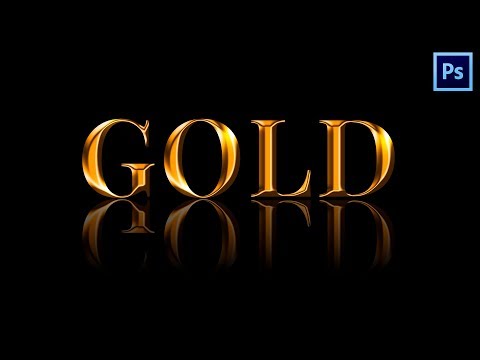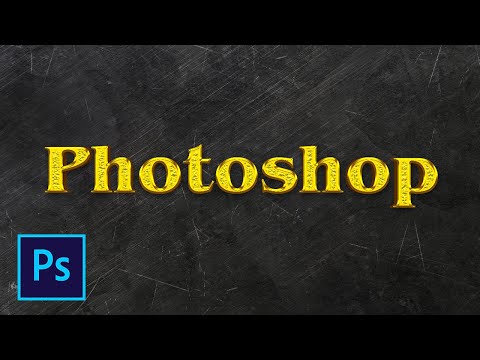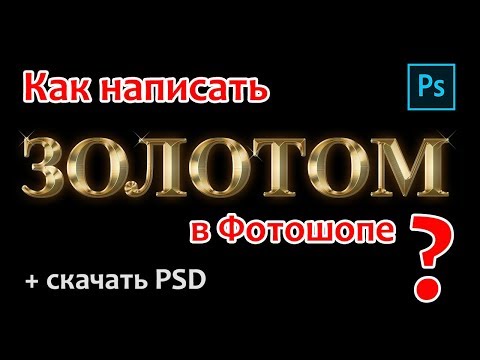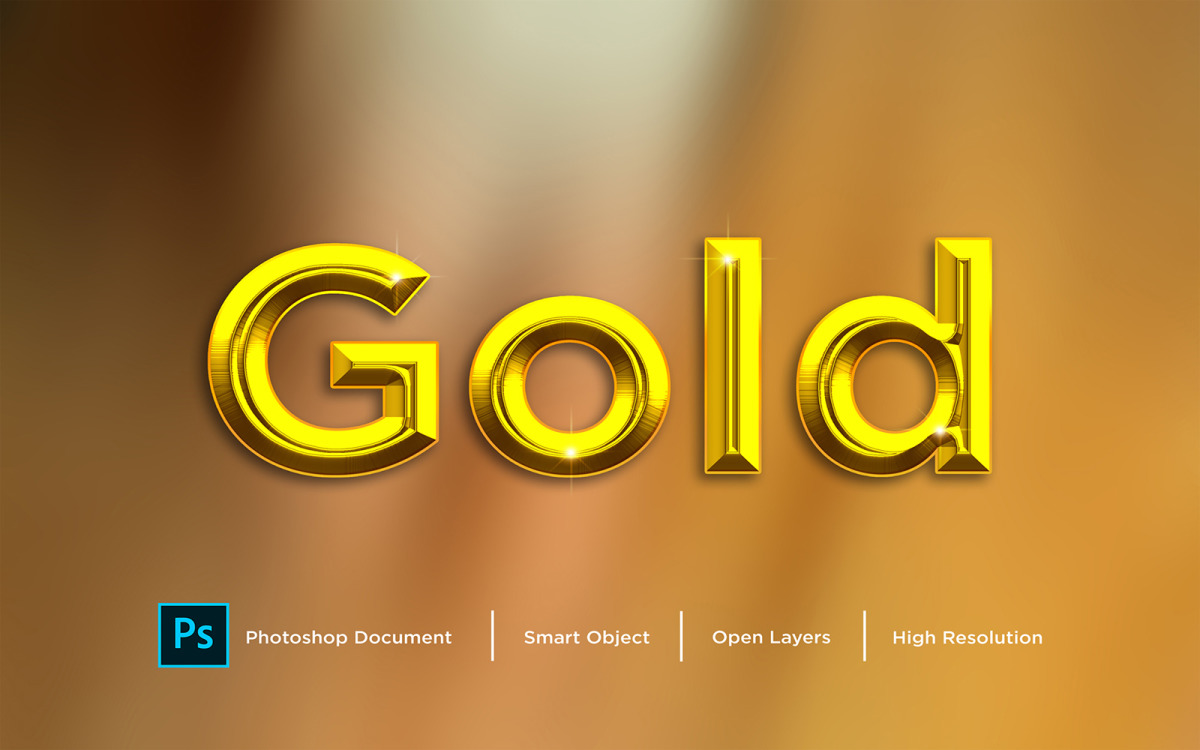
Изящные золотые буквы с эффектом блеска и россыпи
Хотите придать вашему тексту блеск и роскошь золотого шрифта? В этой статье вы найдете подробные инструкции о том, как создать впечатляющий эффект золотого шрифта в программе Adobe Photoshop. Получите исчерпывающие советы и представьте ваш текст в роскошном золотом свете!
Создайте новый документ в программе Adobe Photoshop и выберите желаемый размер и разрешение для вашего текста.
Выберите инструмент Текст (T) и введите ваш текст с выбранным шрифтом. Установите размер шрифта и задайте цвет текста на золотой или близкий к нему.
Добавьте эффекты для создания эффекта золота. Используйте функции Оттенок/Насыщеность и Объемный свет в меню Слой или добавьте стили слоя, такие как Внешняя свечение, Тиснение и Наложение градиента. Экспериментируйте с параметрами, чтобы достичь наилучшего эффекта золотого шрифта.